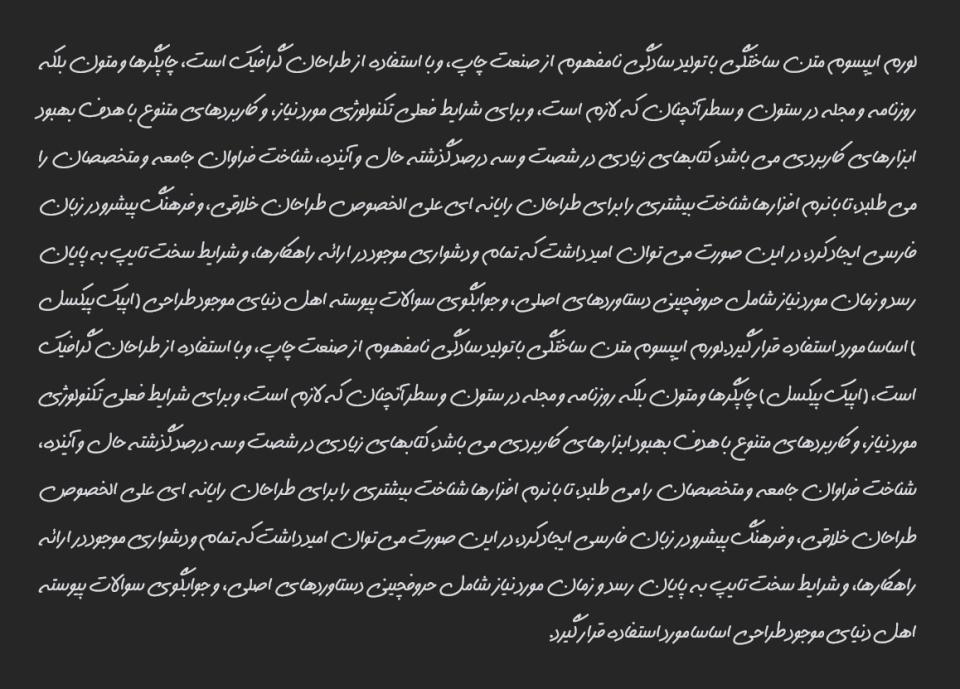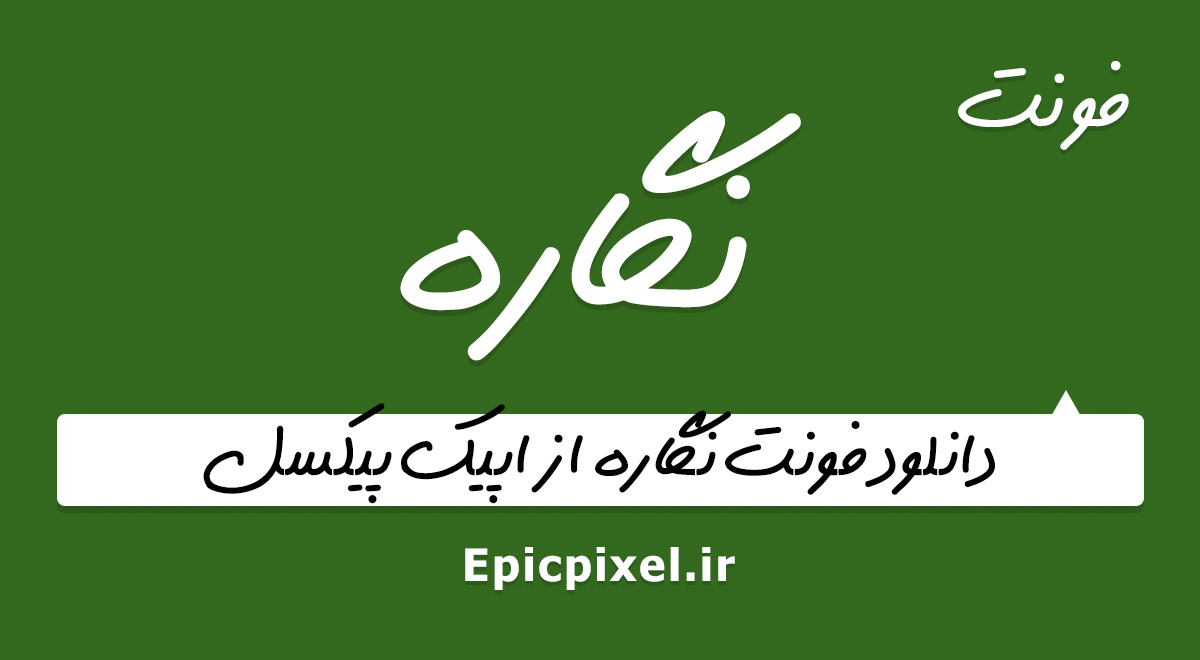
2 فونت نگاره فارسی Negare
فونت نگاره، با الهام از دست نوشته های قدیمی و خاطره انگیز، حس نوستالژی دلنشینی را به طراحی های شما می بخشد. این فونت رایگان، با بازطراحی و رفع نواقص فونت مادر خود، تجربه ای روان و لذت بخش از تایپ فارسی را ارائه می دهد. در طراحی نگاره، تلاش شده تا مشکل خوانایی برخی حروف مانند «س» و «ش» که در نسخه های قدیمی تر دیده می شد، به طور کامل برطرف شود و فرمی خواناتر و چشم نوازتر به خود بگیرند. البته، امکان استفاده از حالت کشیده این حروف به عنوان جایگزین نیز همچنان وجود دارد که به متن شما تنوع و زیبایی بیشتری می بخشد.
یکی از ویژگی های برجسته فونت نگاره، وجود سیلاب های جایگزین خودکار فراوان است که به صورت هوشمندانه در متن اعمال می شوند و به بهبود خوانایی و زیبایی آن کمک شایانی می کنند. این ویژگی به ویژه در متن های طولانی و پاراگراف ها، تاثیر بسزایی دارد و از یکنواختی متن جلوگیری می کند. همچنین، طراحان این فونت، برای افزایش جذابیت بصری، حروف «س» و «ش» کشیده را به صورت جایگزین در نظر گرفته اند که در صورت نیاز می توانید از آن ها استفاده کنید. با این حال، باید توجه داشت که استفاده بیش از حد از این حالت کشیده، ممکن است باعث شلوغی و کاهش خوانایی متن شود.
فونت نگاره در یک وزن و با استایل ماژیکی طراحی شده است که ظاهری صمیمی و دوستانه به متن می بخشد. این ویژگی، آن را برای استفاده در طراحی های غیررسمی، کارت پستال ها، نوشته های شخصی و پروژه هایی که نیاز به حس دست نویس دارند، بسیار مناسب می سازد. در عین حال، همین ویژگی ممکن است استفاده از آن را در متون رسمی و اداری محدود کند. در نهایت، فونت نگاره با ارائه ترکیبی از حس نوستالژی، خوانایی بالا و ویژگی های هوشمندانه، گزینه ای عالی برای طراحانی است که به دنبال فونتی رایگان، زیبا و کاربردی هستند.